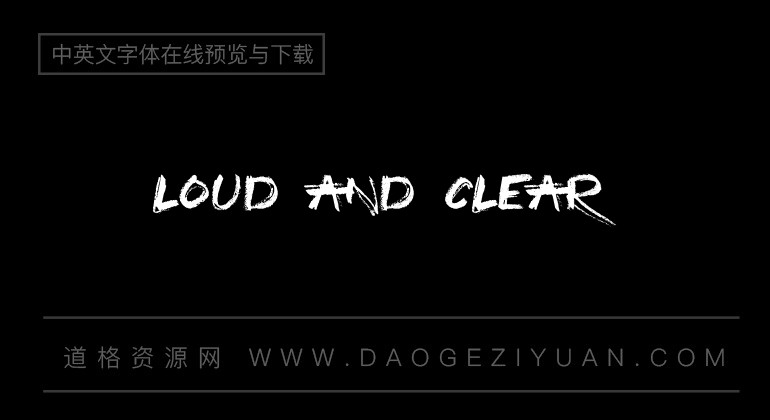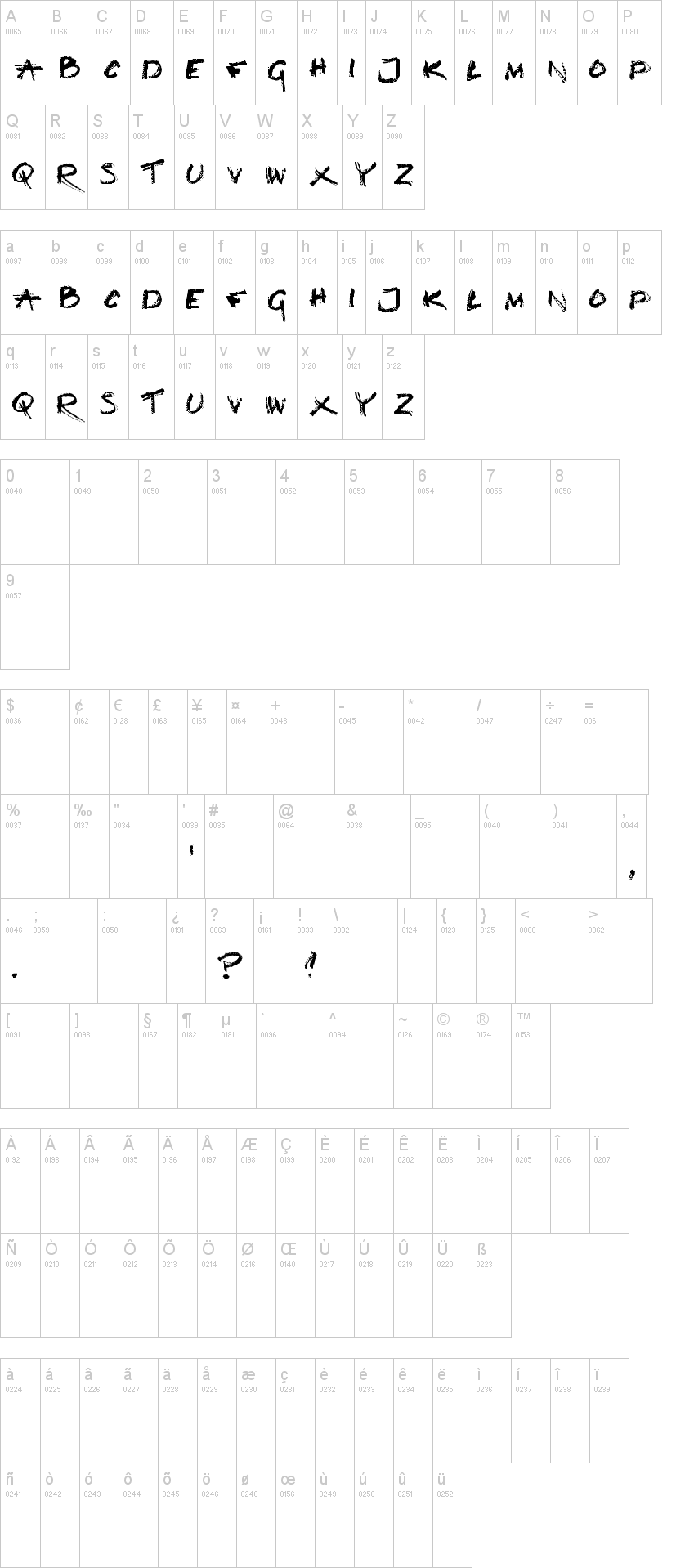
Loud and Clear 是一款美式手写字体,由美国设计师Jeremy Vessey设计,该字体灵感来自于20世纪50年代的街头涂鸦文化。它的特点是充满活力,拥有清晰的笔画和流畅的线条,可以带来温暖而又活泼的感觉。Loud and Clear字体可以用于各种不同的设计项目,如海报、标志、流行服装、印刷品等,可以让设计更加精彩。内容介绍
Loud and Clear是一款非常不错的手写艺术字体,具有很好的视觉感,适合于文化类的宣传设计、商业类品牌的广告和产品包装设计以及个性化文字排版等较多场景。